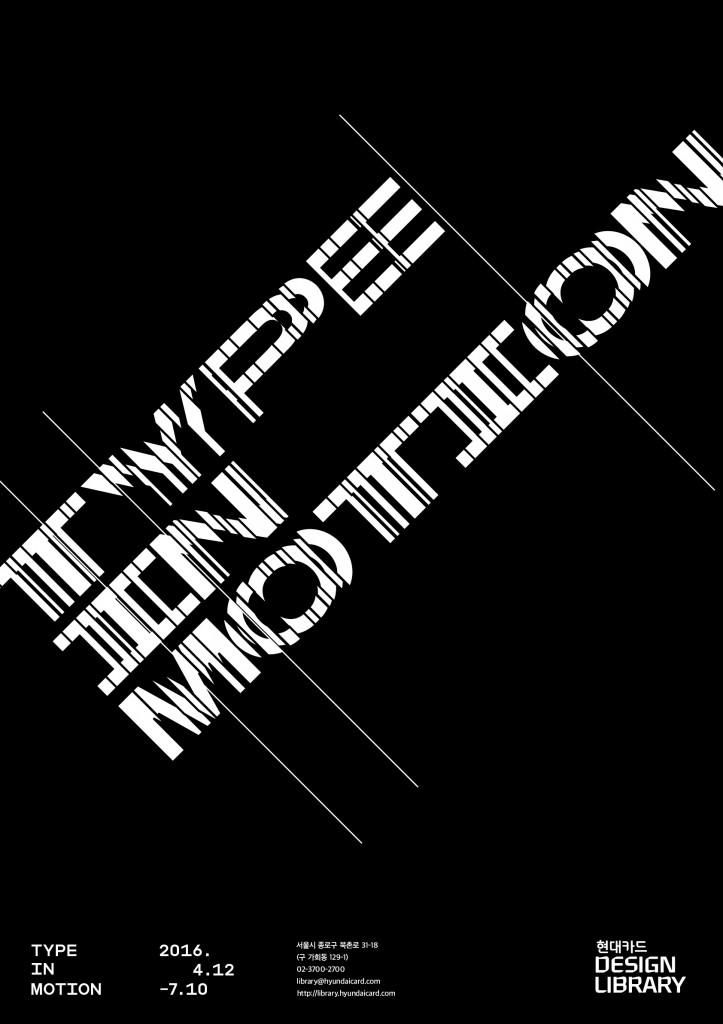
<타입 인 모션 TYPE IN MOTION>전시 : 이토록 역동적인 타이포그래피!
현대카드 디자인 라이브러리에서 열리는 <TYPE IN MOTION>에서 글자는 그 어떤 것보다 강한 생명력을 지니고 꿈틀거리며 살아 숨쉰다. 이처럼 사운드와 모션그래픽과 융합되어 새로운 경험을 선사하는 ‘모션 타이포그래피’는 시대를 상징하는 새로운 형식의 텍스트라 할 수 있겠다.
<타입 인 모션 TYPE IN MOTION> @ 현대카드 디자인 라이브러리
글자는 언제나 차분하다. 정보의 전달이라는 그 본연의 목적에 충실하기 위해 텍스트는 흔들림 없이 단단해야 한다. 정적일 수 밖에 없는 이유다. 타이포그래피도 마찬가지다. 글자를 가지고 디자인하기 때문에 글자의 이런 속성과 맞닿아있다. 약간의 활기를 띠고 좀 더 자유로울 수는 있지만, 여전히 글자의 차분한 인상을 벗어나진 않는다.
이런 통념을 깨는 전시가 있다. 바로 현대카드 디자인 라이브러리에서 열리는 <TYPE IN MOTION>이다. 이 전시에서 글자는 그 어떤 것보다 강한 생명력을 지니고 꿈틀거리며 살아 숨쉰다. 화려한 영상보다 더 뚜렷하고, 흥겨운 리듬보다 더 발랄하다. 그동안 숨겨왔던 자신의 끼를 글자는 마음껏 드러낸다. 이토록 역동적인 타이포그래피라니! 글자가 주인공이 되어 활약하는 장면을 우리는 이 전시에서 목격할 수 있다. 이처럼 사운드와 모션그래픽과 융합되어 새로운 경험을 선사하는 ‘모션 타이포그래피‘는 시대를 상징하는 새로운 형식의 텍스트라 할 수 있겠다.
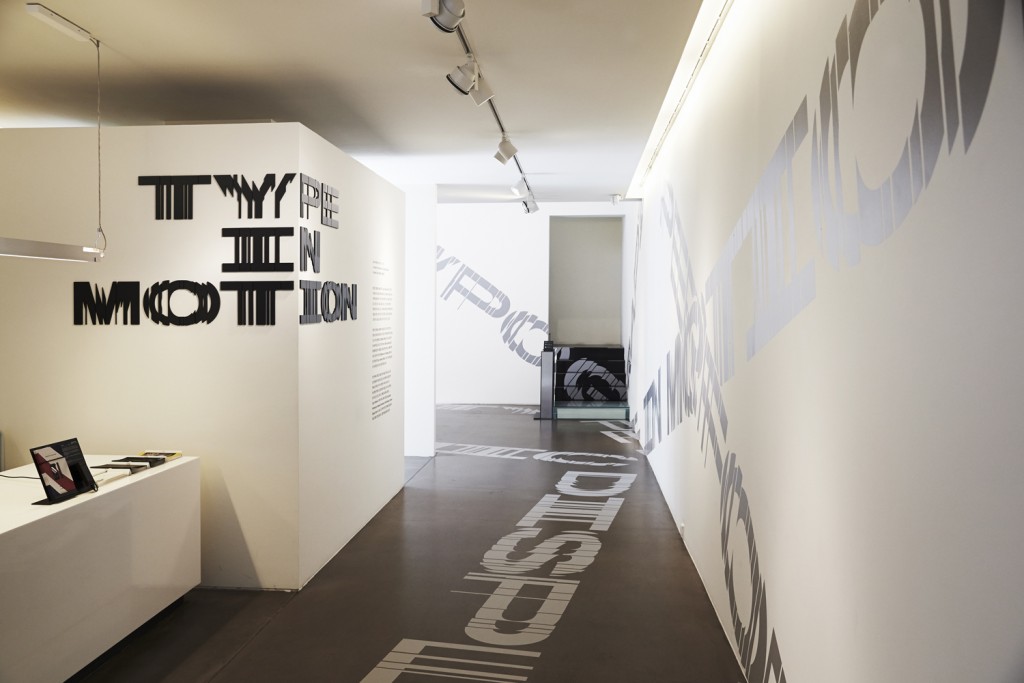
전시장 입구부터 글자들이 꿈틀댄다
총 28개의 작품을 온전히 감상하려면 한 시간 반 남짓 걸리지만, 다양한 개성의 작품을 공통된 디자인 테마로 나눠 소개해서인지 어렵지 않게 몰입할 수 있다. 2011년 취리히 디자인 미술관에서 처음 기획된 본래의 전시를 새로운 디자인 테마를 정해 재구성하고, 이에 맞춰 작품들을 추가했다고 한다. ‘Typographic Performance’, ‘Animated Information’, ‘Word Montage’, ‘Dynamic Display’, ‘Voice of a Text’. 5개 카테고리의 타이틀만 읽어봐도 이 전시의 전체적인 맥락을 알 수 있다.
새롭게 추가된 작품으로는 오픈 소스를 활용한 영상 작품 <Thank You Market>(2015)을 비롯해 뉴욕에서 모션 그래픽 디자이너로 활동하고 있는 김상욱의 작품 <Explore. Dream. Discover>(2013), 영국 대표적인 록밴드 ‘The Rolling Stones’의 음악을 시각적 이미지로 표현한 뮤직비디오 <Doom & Gloom>(2013) 등이 있는데 아래에서 일부 이미지를 확인할 수 있다.
‘CXEMA’ by PolyEsther & Kabutogani
‘The Child’ by H5
‘Thank You Market’ by Creative Destruction
‘Anonymous | Hacktivism’ by Saava Tsekmes
‘Stranger than Fiction’ by MK12
‘Explore. Dream. Discover’ BY Sang Wook Kim
작품 밖에서도 글자는 역동한다. 전시공간 곳곳을 누비는 타이포그래피가 그것이다. 국내 대표적인 타이포그래피 디자이너인 정진열 교수(국민대 시각디자인과)가 전시의 테마에 맞춰 디자인한 ‘월 텍스트’를 공간 전체에 구현했다. 글자는 정적이며 평면적이라는 고정관념을 과감하게 뒤흔든다. 텍스트를 분절하고 공간에 따라 뒤틀면서 영상 작품 속에서 꿈틀대던 에너지를 그대로 살려 시각화했다. 전시의 의도를 공간에서 자연스럽게 드러내며 관람객들의 이해를 직관적으로 돕는다.
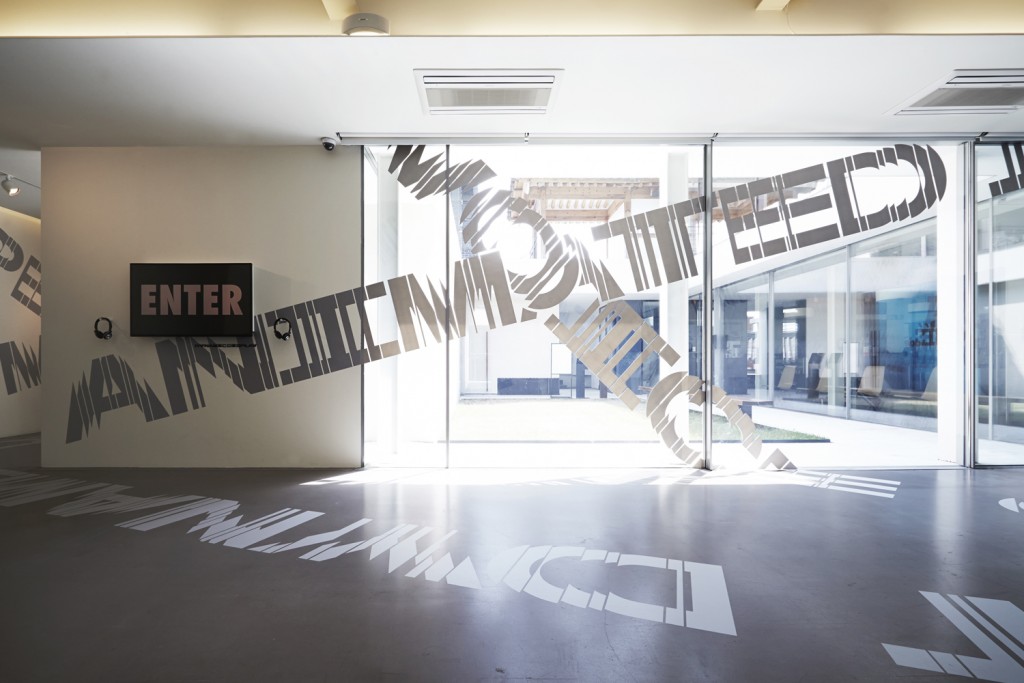
전시공간 전체에 구현된 월 텍스트
이 전시의 또 하나의 부록은, 디자인 도서 15,000권을 소장하고 있는 디자인 라이브러리이다. 전시를 감상하고 한 층만 위로 올라가면, 지금까지 신나게 뛰놀던 텍스트들이 언제 그랬냐는 듯 다시 책으로 들어가 누군가의 손길을 차분히 기다리고 있는 풍경은, 전시와 대비되어서인지 더욱 인상적이다. 디자인의 과거와 현재를 엿볼 수 있도록 세심하게 배치된 공간을 거닐다 보면 디자인의 미래를 상상해 볼 수 있을 것이다.
온 생명이 약동하는 이 봄, 텍스트의 약동을 감상해볼 수 있는 이 전시를 추천하며, 가장 흥겨웠던 작품 하나를 여기에 옮겨본다.